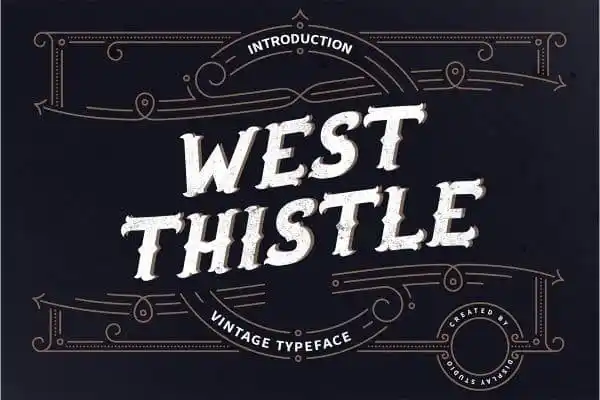
West Thistle Display Font – Download Grátis
Descobrimos uma nova fonte chamada West Thistle Display, especialmente projetada para letras pesadas ou espessas. Esta fonte foi criada pela Display Studio e é perfeita para aplicação em várias mídias como capa de livros, revistas, jornais, banners publicitários, menus, páginas de websites e até mesmo como logomarca. West Thistle Display é perfeitamente adequado a quem busca uma fonte que dê um toque especial à sua marca ou design gráfico. Seja você criador de livros, designer web ou artista freelance, esta font pode ser ideal para qualquer projeto que exige letras robustas e impactantes. Para aqueles que buscam algo mais peculiar na categoria de Blackletter Fonts, este é o tipo de fonte a adicionar ao seu arsenal de ferramentas. West Thistle Display oferece uma aparência única que se destacará em designs gráficos que exigem um toque especial e único. Seja usado para criar capas memoráveis ou menu sofisticados, sua elegância e força garantirão que seu trabalho fique impecável e perfeito na primeira vista. O designer 99designs compartilhou esta fonte com o público, proporcionando uma ferramenta de design poderosa para aqueles que querem trazer a suas criações um toque autêntico e diferenciado.